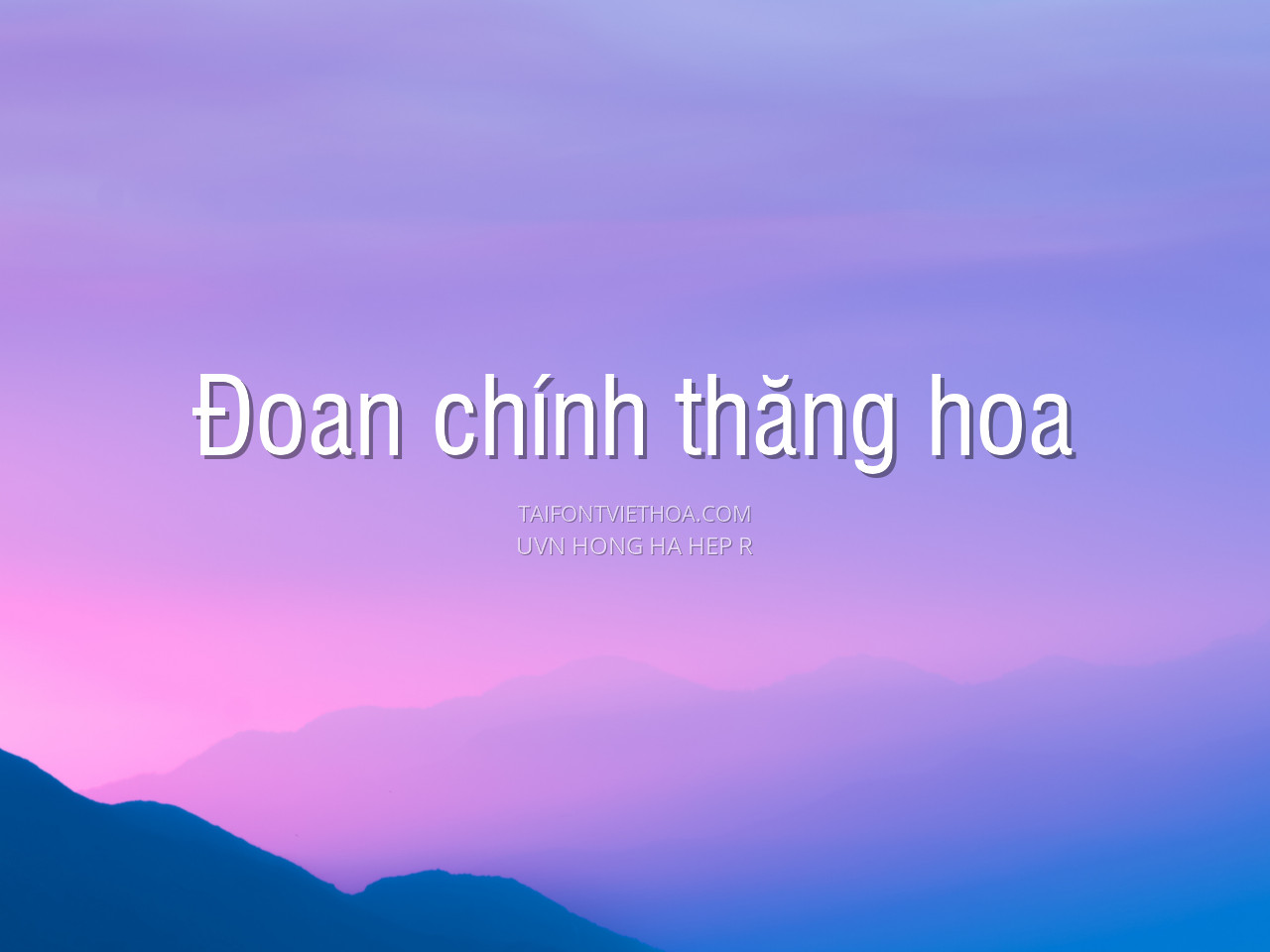
Giới thiệu về font UVN Hong Ha Hep
UVN Hong Ha Hep là biến thể thu gọn (condensed) của bộ font UVN Hong Ha nổi tiếng, mang lại cảm giác thanh thoát, gọn gàng nhưng vẫn giữ được sự trang nghiêm và truyền thống vốn có. Với tỷ lệ chiều ngang hẹp lại, font này đặc biệt phù hợp cho các thiết kế cần tiết kiệm không gian mà vẫn đảm bảo độ rõ ràng và nghiêm túc. UVN Hong Ha Hep được sưu tầm và chia sẻ bởi thành viên Font Chuẩn, và được taifontviethoa.com chọn lọc để ứng dụng trong nhiều dự án in ấn, giáo dục và truyền thông cộng đồng nơi không gian trình bày bị giới hạn.
Đặc điểm thiết kế và ứng dụng của UVN Hong Ha Hep
Font UVN Hong Ha Hep thuộc nhóm sans-serif, có kiểu dáng hẹp nhưng giữ nguyên chiều cao chữ tiêu chuẩn, từ đó tối ưu diện tích trình bày mà không làm giảm tính thẩm mỹ. Nét chữ rõ ràng, độ dày đồng đều và dễ nhìn ở mọi cỡ chữ giúp font này thích hợp cho các tài liệu văn bản dài, bảng biểu hoặc trang tiêu đề trang trọng. Font hỗ trợ tiếng Việt đầy đủ, tương thích tốt với các phần mềm thiết kế hiện đại.
Ứng dụng lý tưởng: giáo trình, biểu mẫu, tiêu đề tài liệu, infographics giáo dục, slide thuyết trình. Ngành nghề phù hợp: giáo dục, xuất bản, hành chính, thiết kế văn bản chuyên môn, trình bày báo cáo và tài liệu truyền thống.